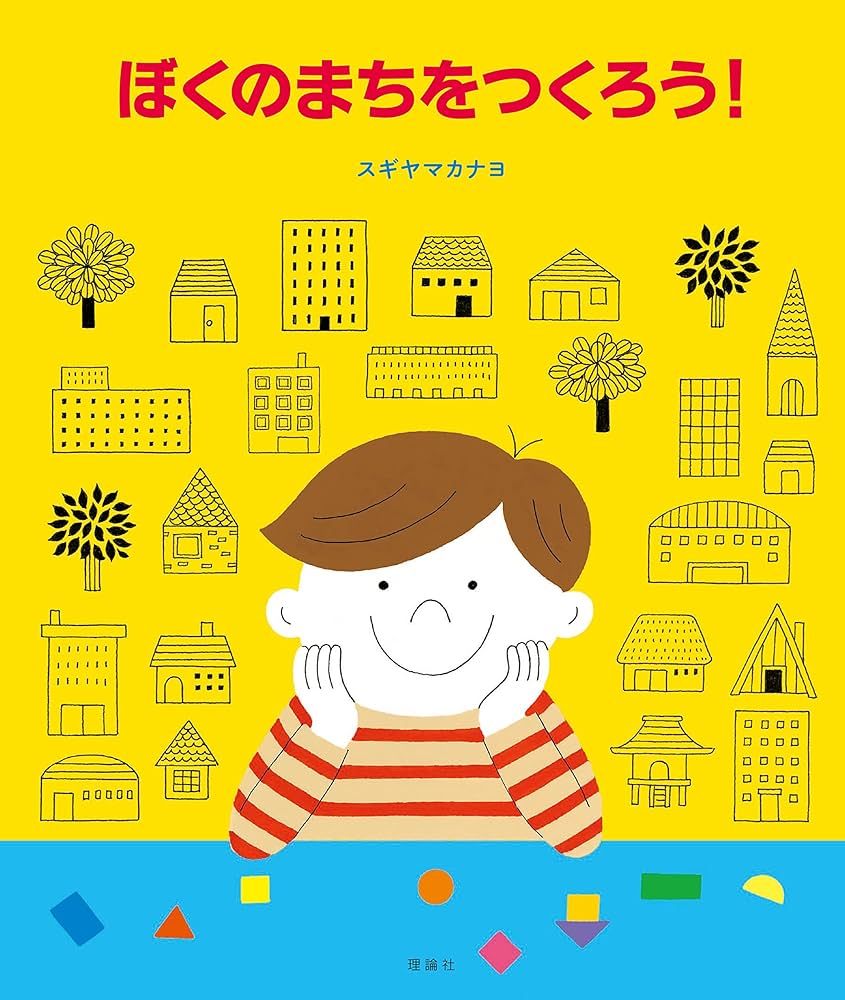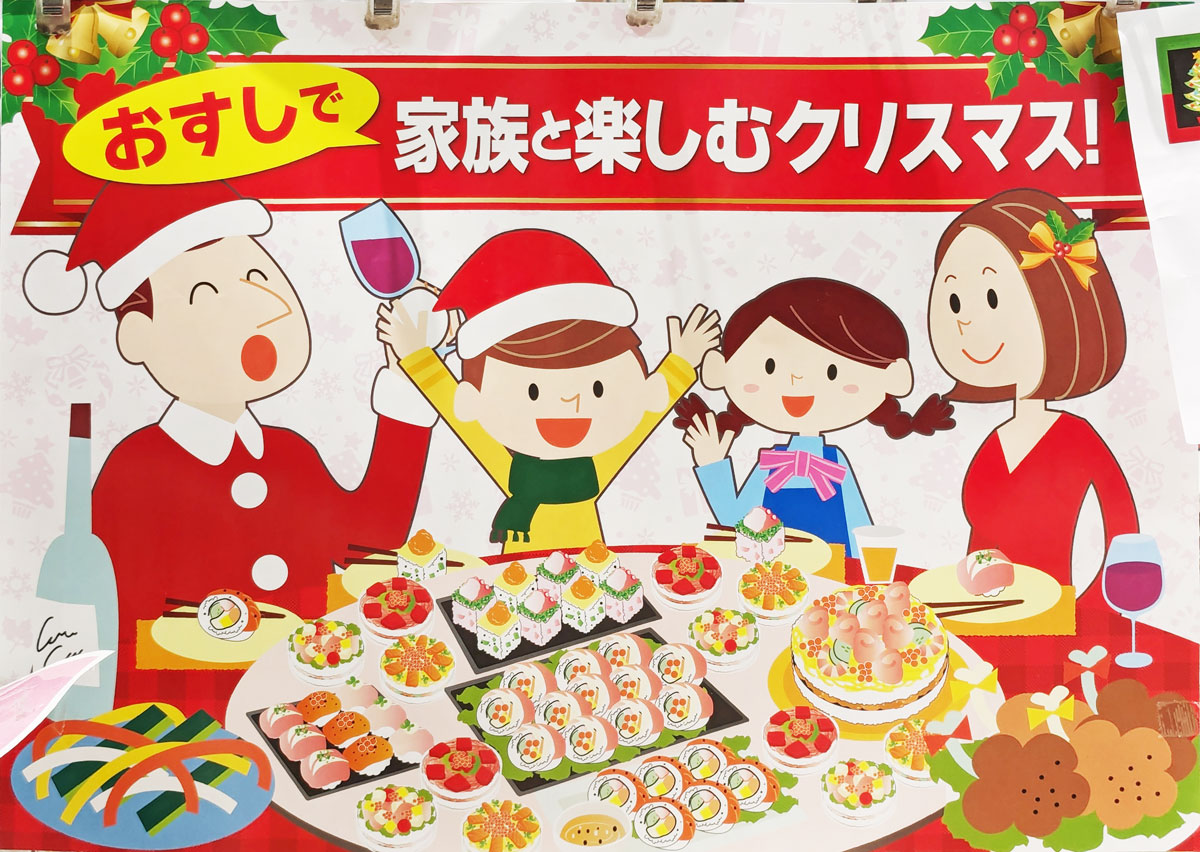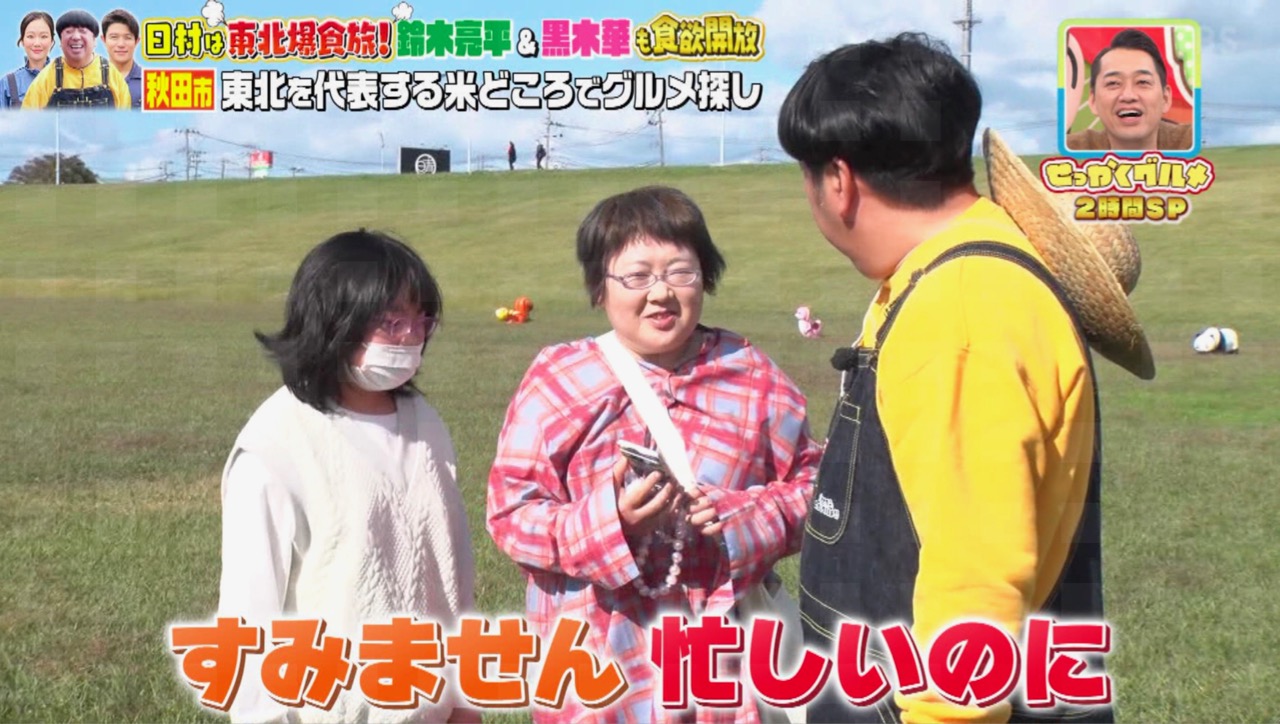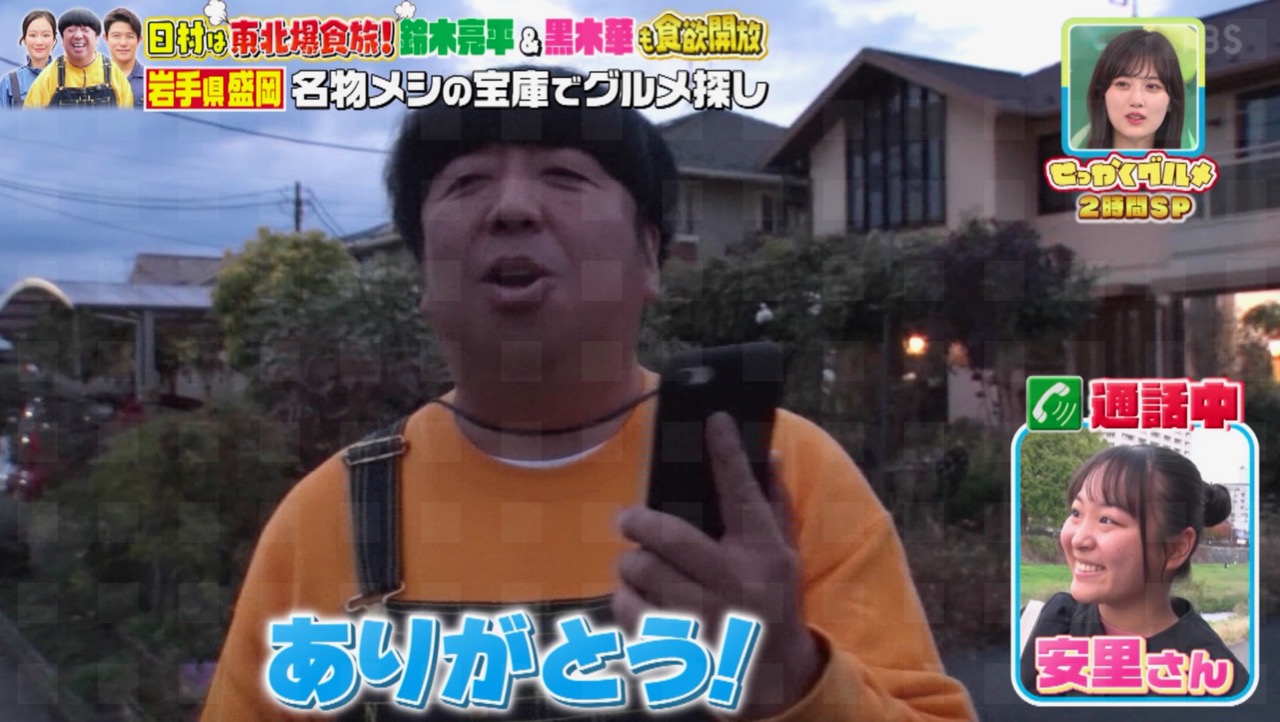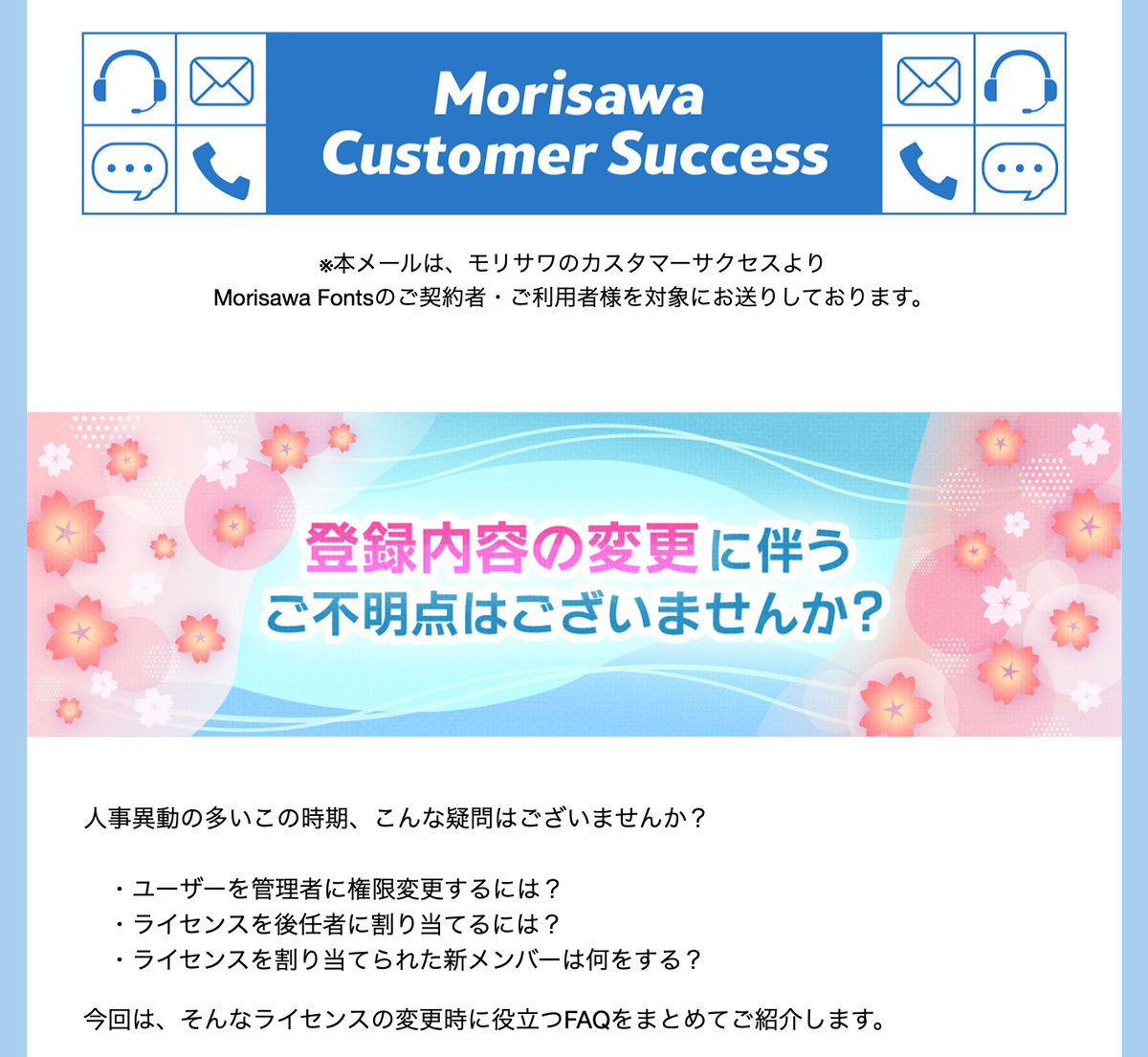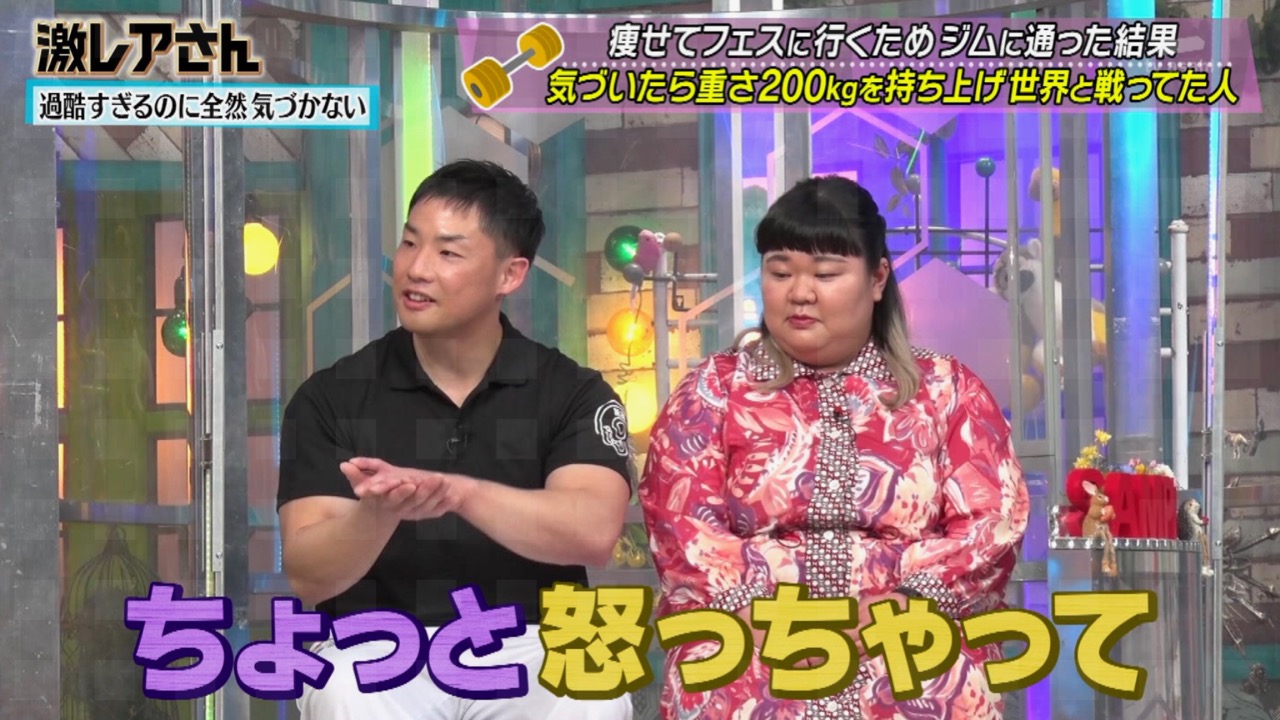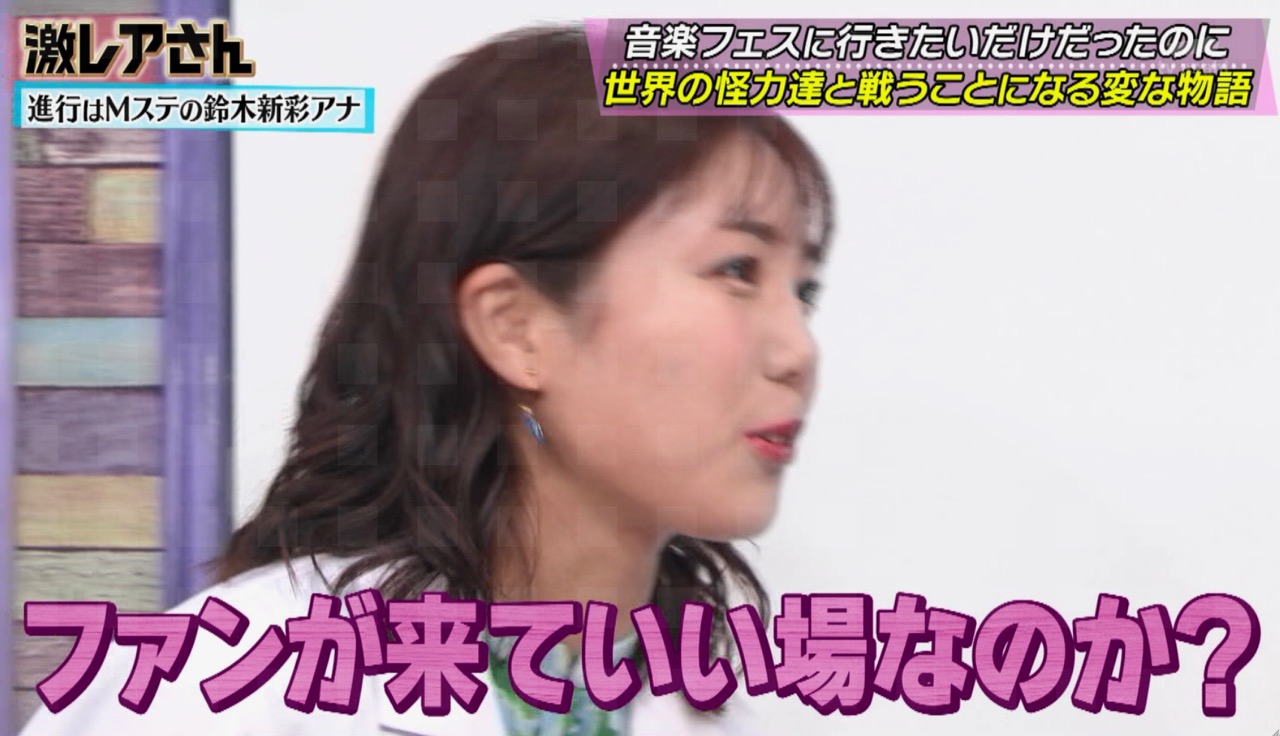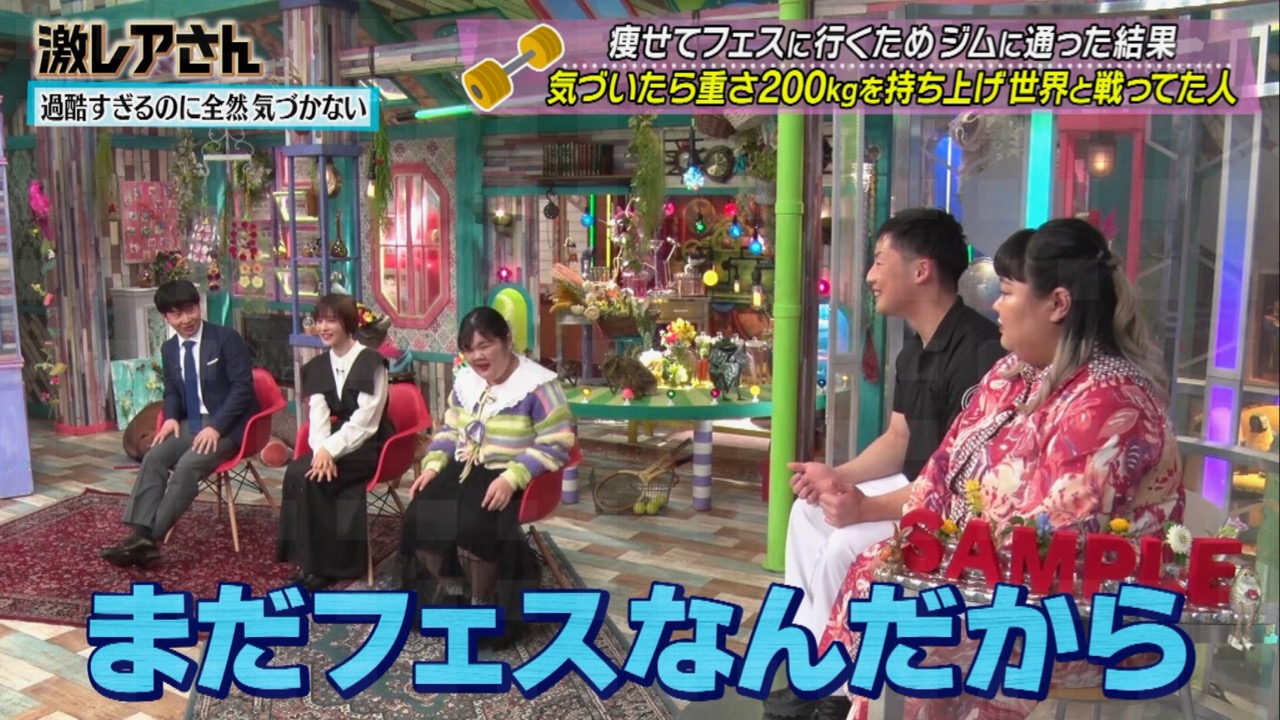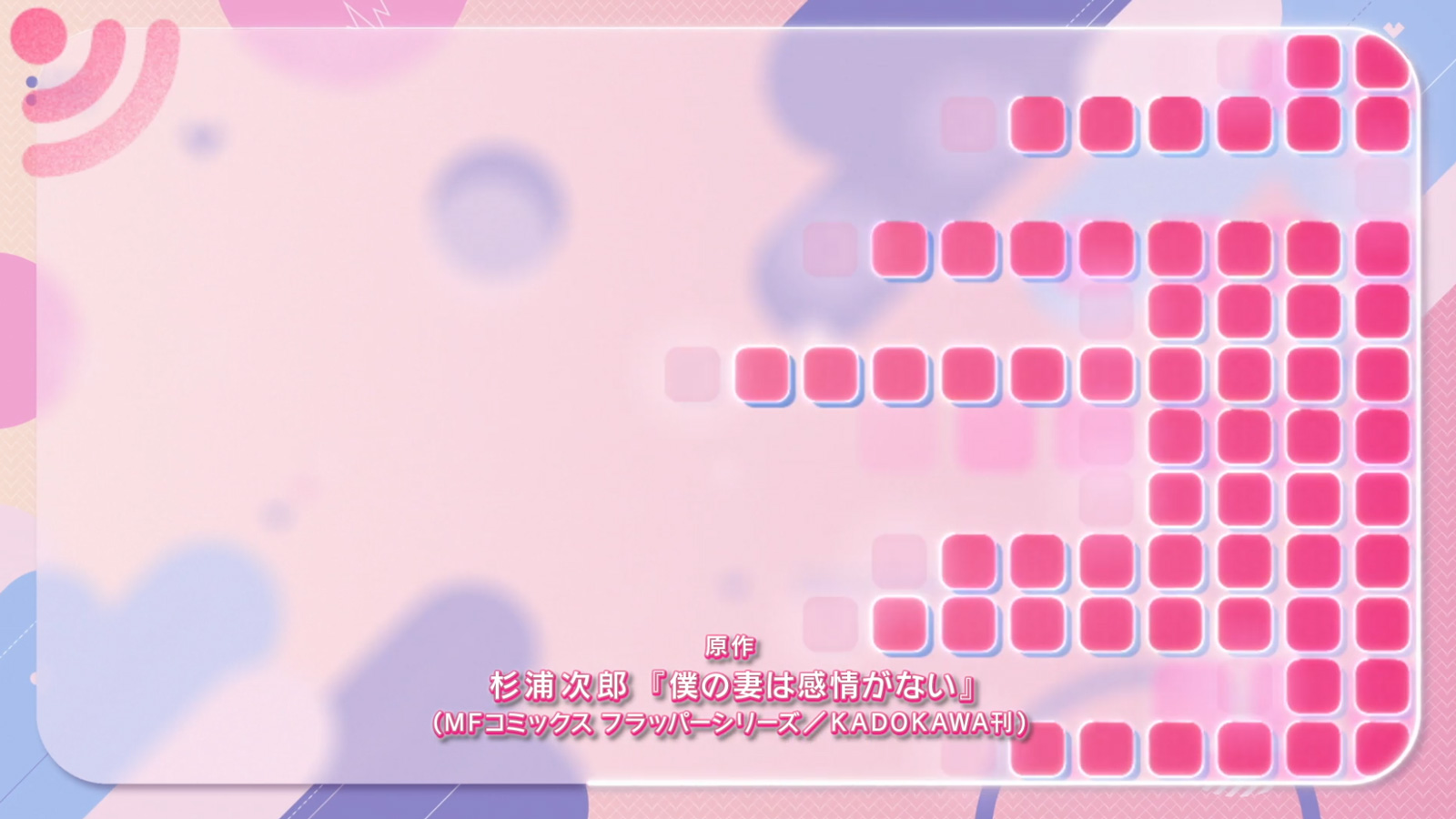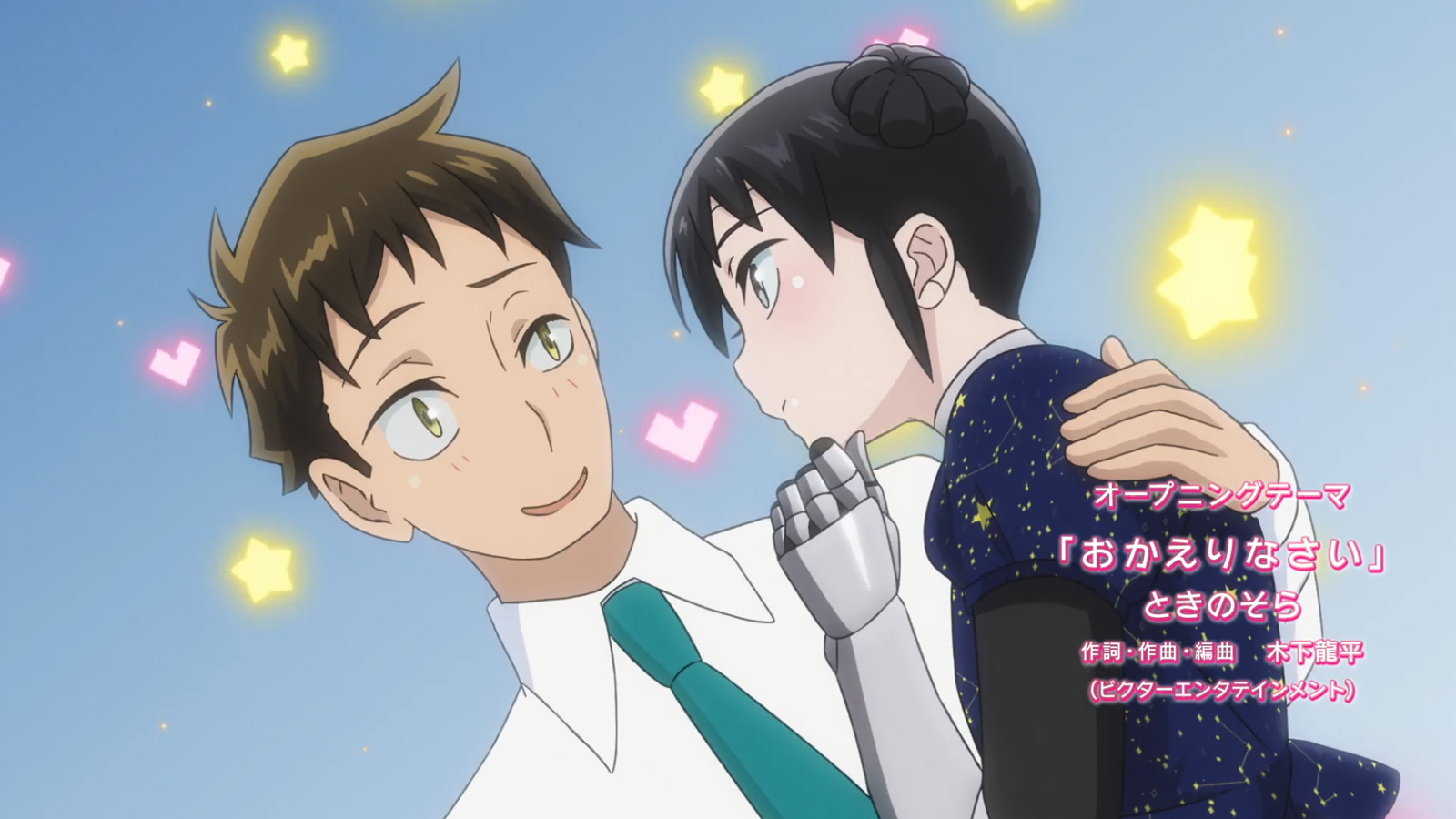
「これだけですっきりキレイ!」がわんぱくルイカ。
それ以外の部分は、ニタラゴルイカが使われているようだ。
キットカットのクリスマスキャンペーン画像。
これも…。
ウチも買い置きしている商品。
カレー商品。
「かんずり屋さんのゆず」の部分。
「カレー」部分は、えれがんと書体。
漫画界のアカデミー賞と言われる「アイズナー賞」に殿堂入りしたそうです。
カルビーの腸内環境を整えるグラノーラの広告画像。
このサイトでは使われてませんが…。
アニメ化もされた漫画「私に天使が舞い降りた!」の完結記念イベントの広告媒体でわんぱくルイカが使われています。
最後にこれも。
ほとんどの文字がわんぱくルイカです。
たくさん使われていますね!
第3回 カエルクリエイターズフェスタ。
こちらは前回のやつかな。
今年も使ってくれている…。
TBSの連続ドラマ「三人夫婦」
しっかりと漢字まで「わんぱくルイカ」が使われている。
余計な装飾のないサンセリフ書体は、短時間で消えていく映像内の文字として使いやすいのだろう…。
もうひとつ。
これも、この番組の番宣動画だな…。
まだあった…。